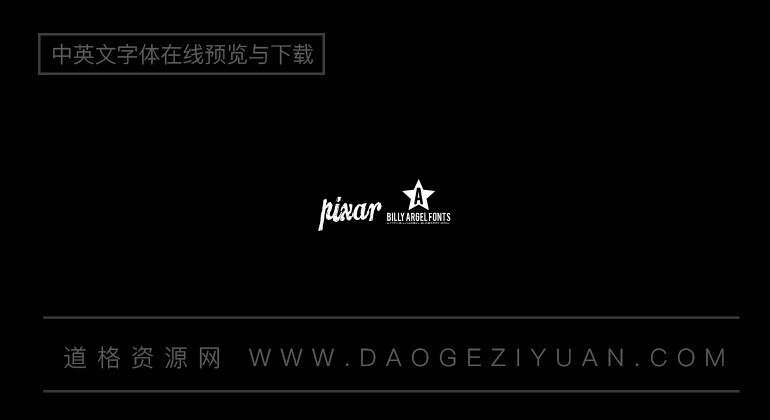
Pixar 1
Pixar 1 字体是由 Pixar Animation Studios 设计的一种字体,通常用于其电影、动画和品牌标志中。它的设计灵感来自于手写风格,具有温暖、亲切的感觉。 Pixar 1 字体由两种字体组成:Pixar Regular 和 Pixar Bold。它们都是无衬线字体,具有类似于手写字的特征,包括不规则的笔画和一些卡通风格的元素。Pixar Regular 字体主要用于电影和动画中的标题和标语,而 Pixar Bold 字体通常用于品牌标志和其他需要强调的文本。 总的来说,Pixar 1 字体是一种独特的字体,既具有手写的感觉,又适用于卡通和动画的设计风格。
Pixar 1是一款非常不错的手写艺术字体,具有很好的视觉感,适合于文化类的宣传设计、商业类品牌的广告和产品包装设计以及个性化文字排版等较多场景。